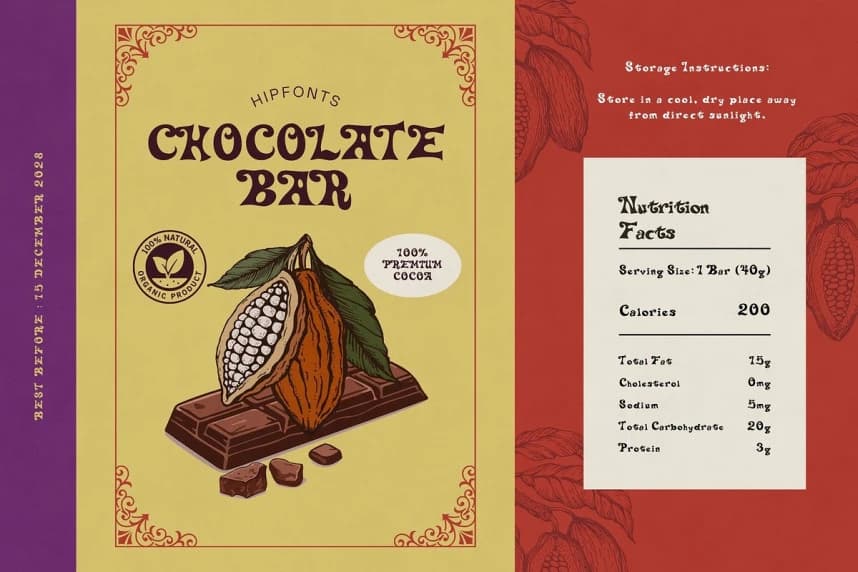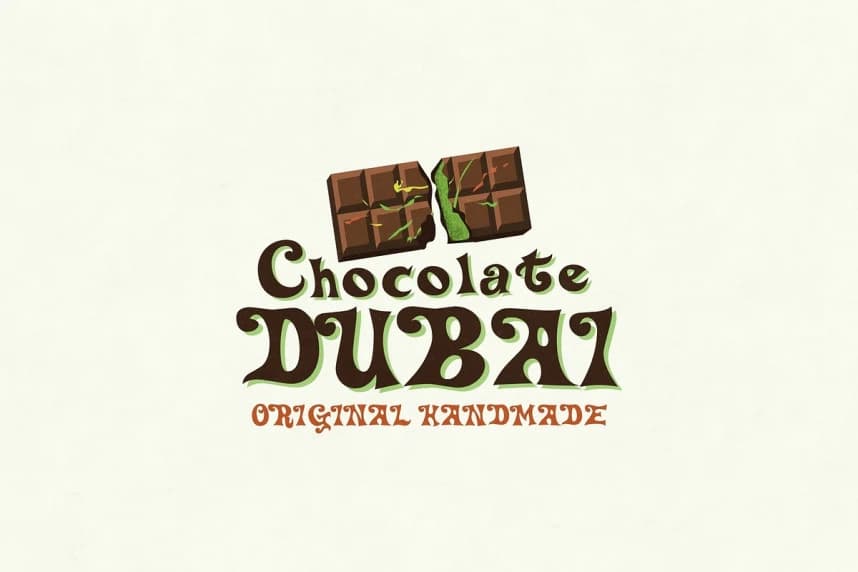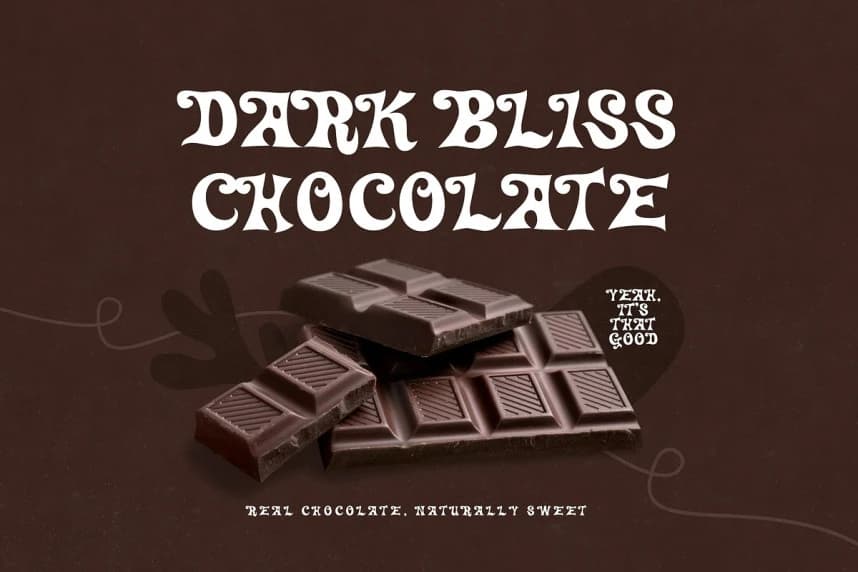
Caramel Kingdom Yazı Tipi
Caramel Kingdom Font - Bu hayal gücü yüksek ve oyunbaz serif yazı tipi, herhangi bir projeye büyülü, eğlence dolu bir çekicilik katıyor ve bu da onu şeker, çikolata ve tatlılar için marka oluşturma, ambalaj ve tanıtım materyalleri açısından mükemmel hale getiriyor.
Caramel Kingdom Font - Bu oyunbaz ve büyüleyici bir serif fontu, her projeye sihirli ve eğlence dolu bir çekicilik katar; şekerlemeler, çikolata ve tatlılar için markalaşma, ambalaj ve tanıtım materyalleri açısından mükemmel hale getirir.